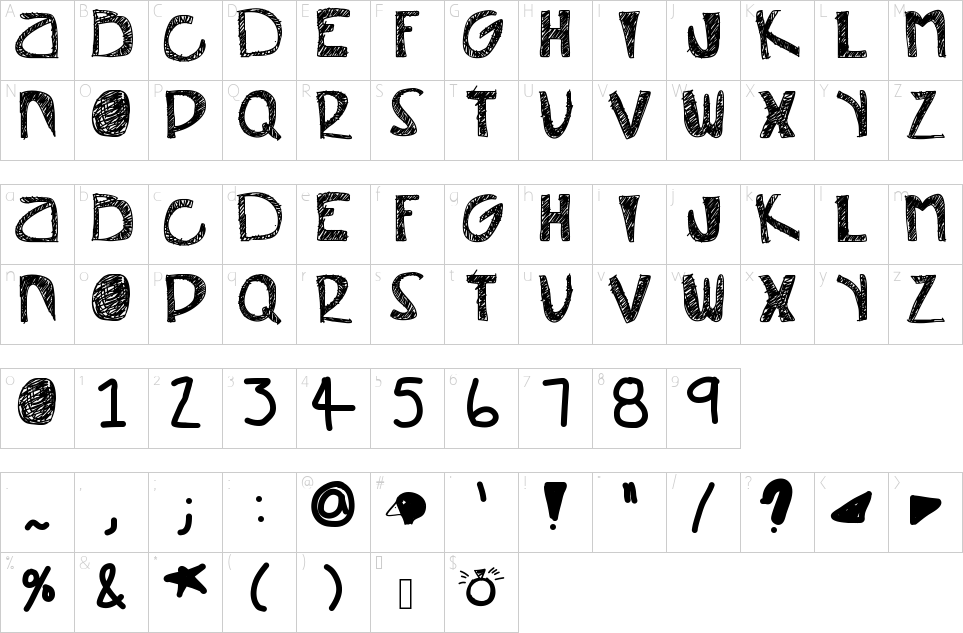
A fonte Misunderstood é uma escolha inspirada para quem procura algo único e distintivo. Desenvolvida por Des Gomez, esta fonte é ideal para projetos criativos que buscam um toque diferente na composição de textos. Com seus traços distintos e sutis, Misunderstood pode fazer sua marca e deixar um impacto forte em qualquer projeto de design. Foi baixada 4,893 vezes, mostrando a sua popularidade como uma fonte única e versátil. A sua adição ao seu arsenal de fontes pode fornecer aquele toque especial que seu projeto precisa. Descubra o poder de Misunderstood para personalizar seu design de fonte, sem gastar muito.